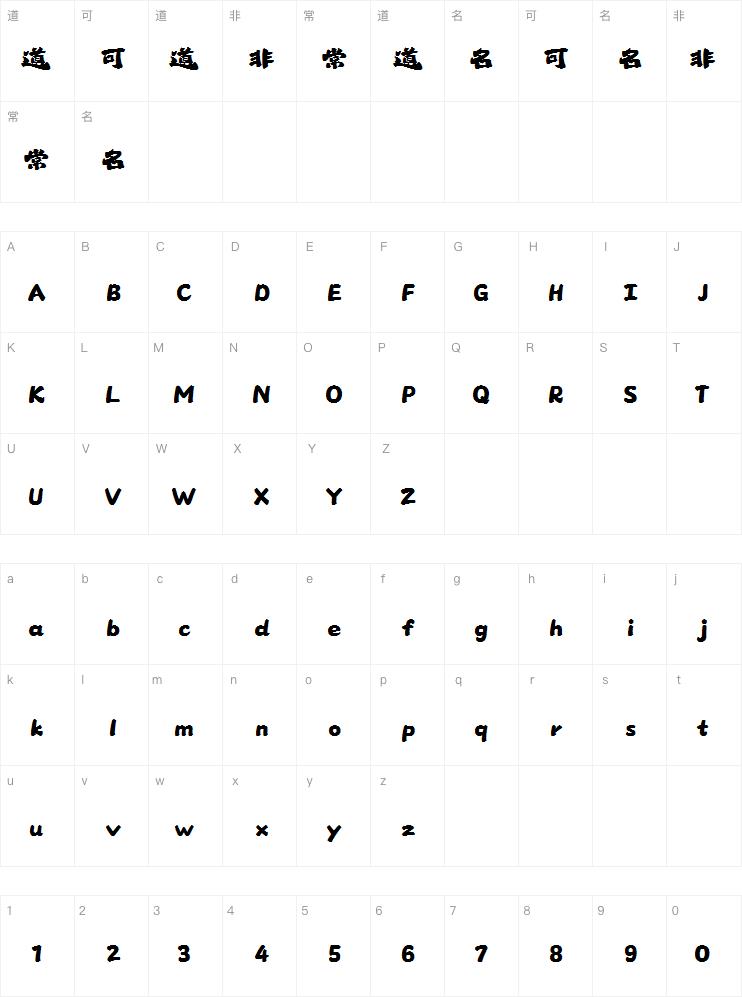
山海凌云志,是一款全新的字体,包含简繁汉字9169个,符号200+个,是一款大字榜书字体。该字体雄健有力,非常醒目,充满了稳重感和设计感。古朴浑厚,笔画与字形间透露着书法运笔的古雅和刚劲的特点,在浑厚的同时而又极富张力,桀骜不驯的特性,霸气外露。它的笔画充满力量感,组合搭配极富强烈的节奏感,字体字形随笔画多少、结构布局不同而大小不一,各个字的大小随字形的不同而呈现不同的大小,但是在变化中寻求平衡,使得整个字体更具有手写感的温度和节奏感。在粗细的纵横间,拥有非常规的张力特性。从而使得该字体字形在浑厚的同时而又极富张力。它的笔画充满力量感的同时,又蕴含着朴拙感。在粗细的纵横间,拥有非常规的张力特性。笔画的书法运笔笔势效果使字体的气息更加流畅,笔画间的关系密不可分,同时也增加了字体的自由洒脱之感。这款字体古韵悠扬而不失灵动,静中有动,收放有序,适合作为标题字体应用于书籍封面、影视标题、展览广告等多种场景。